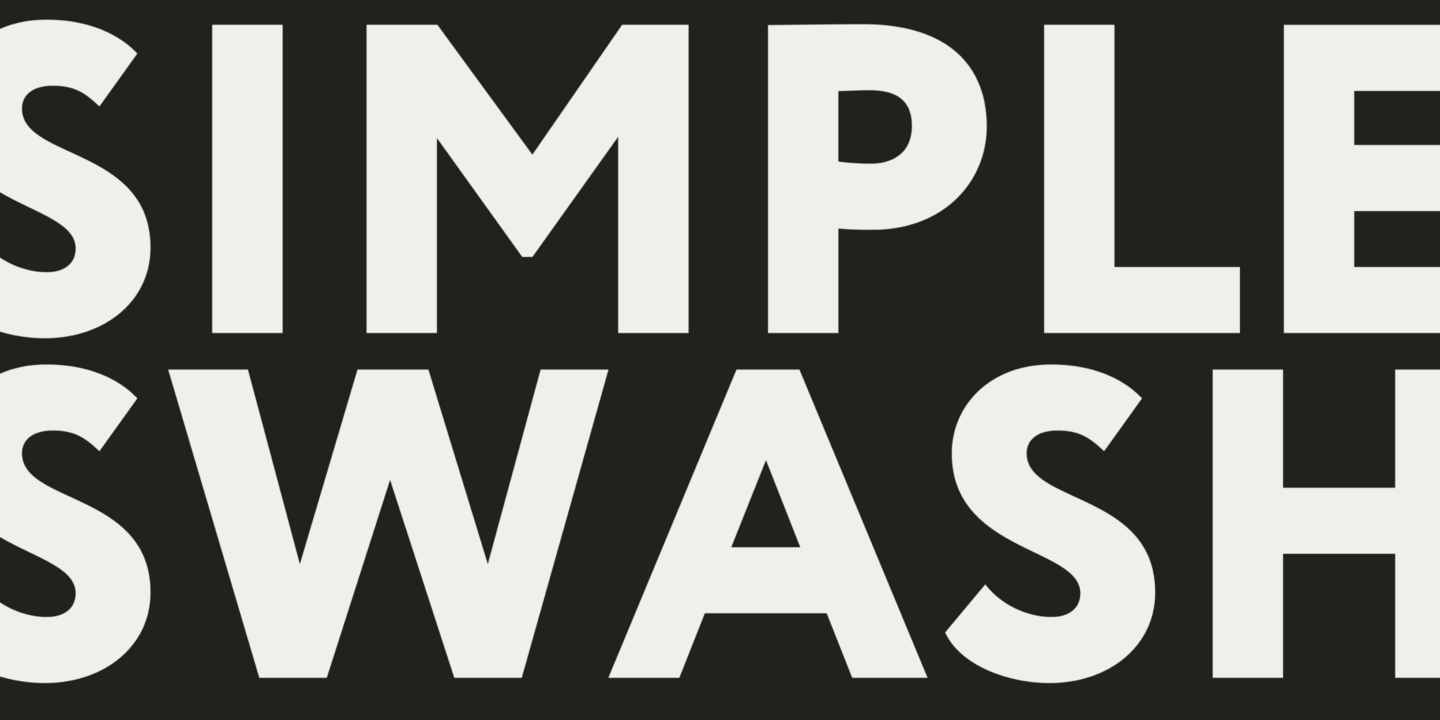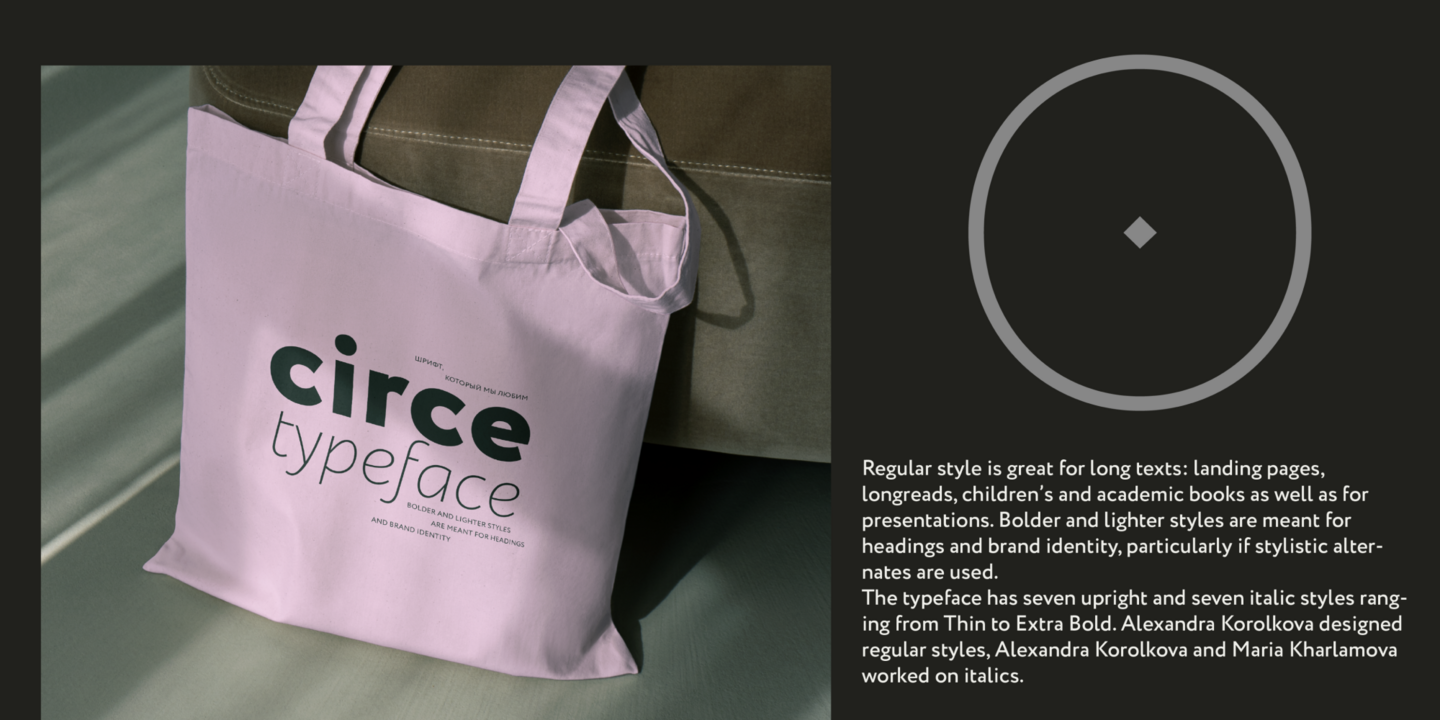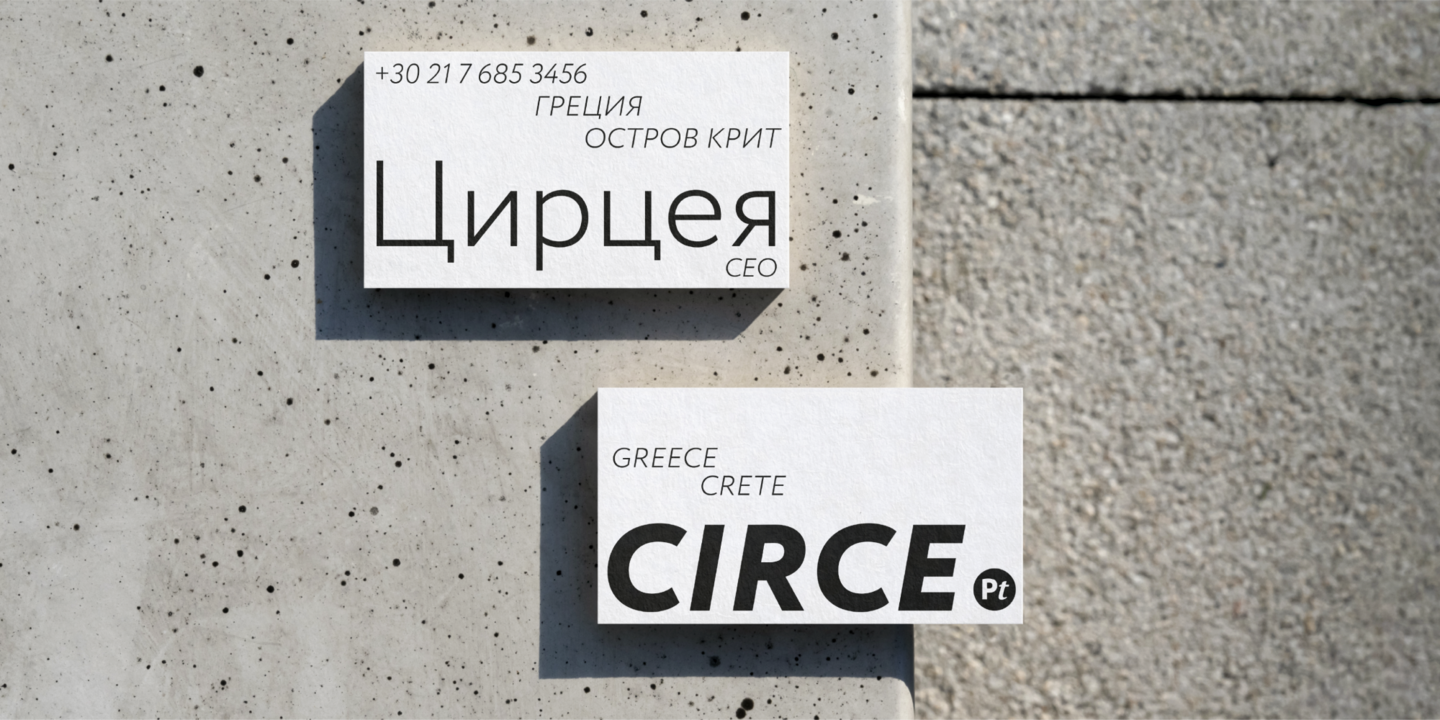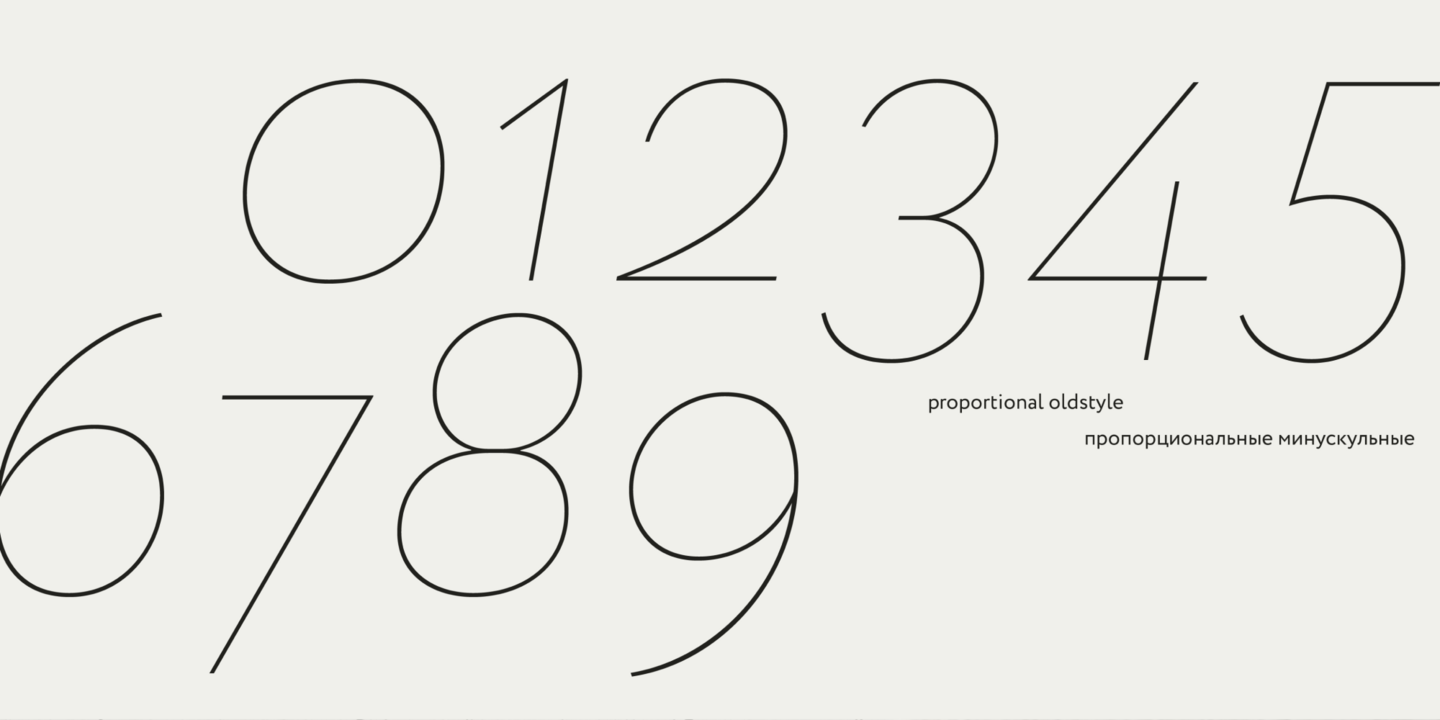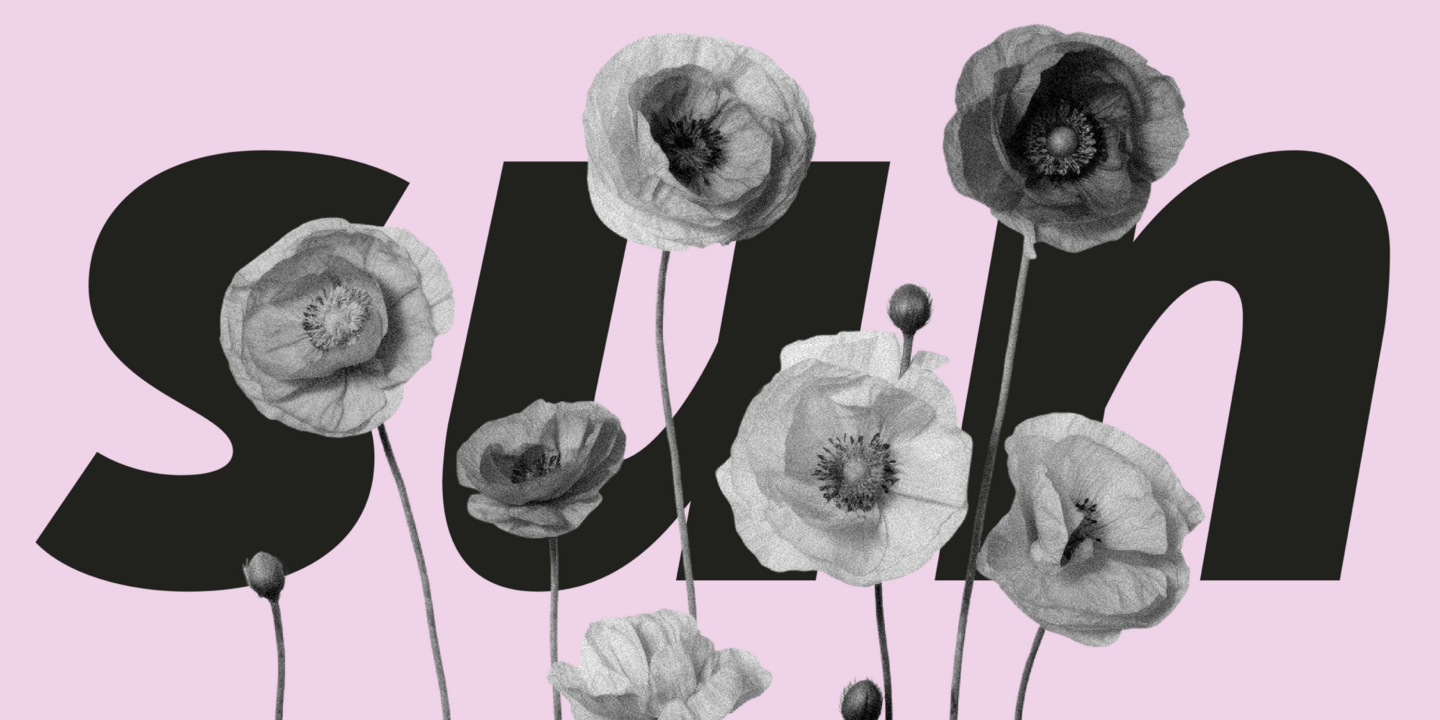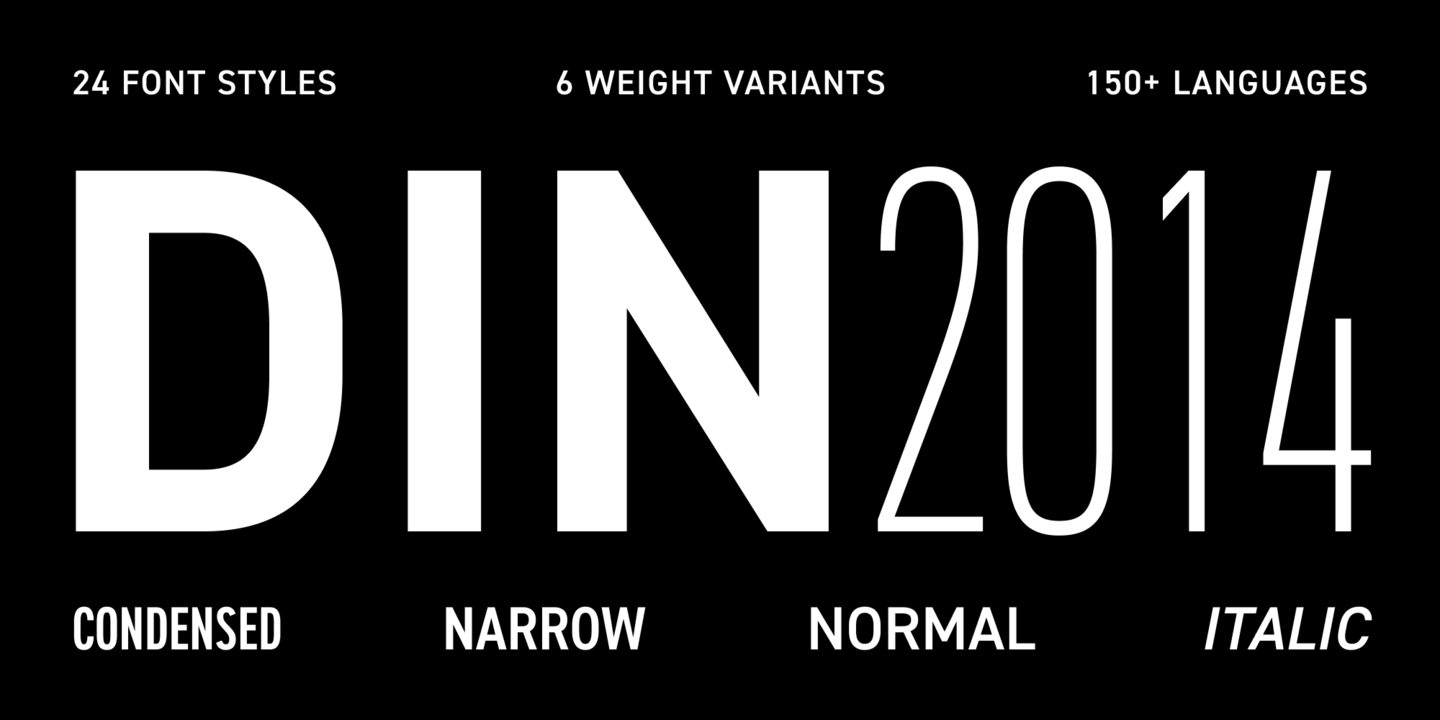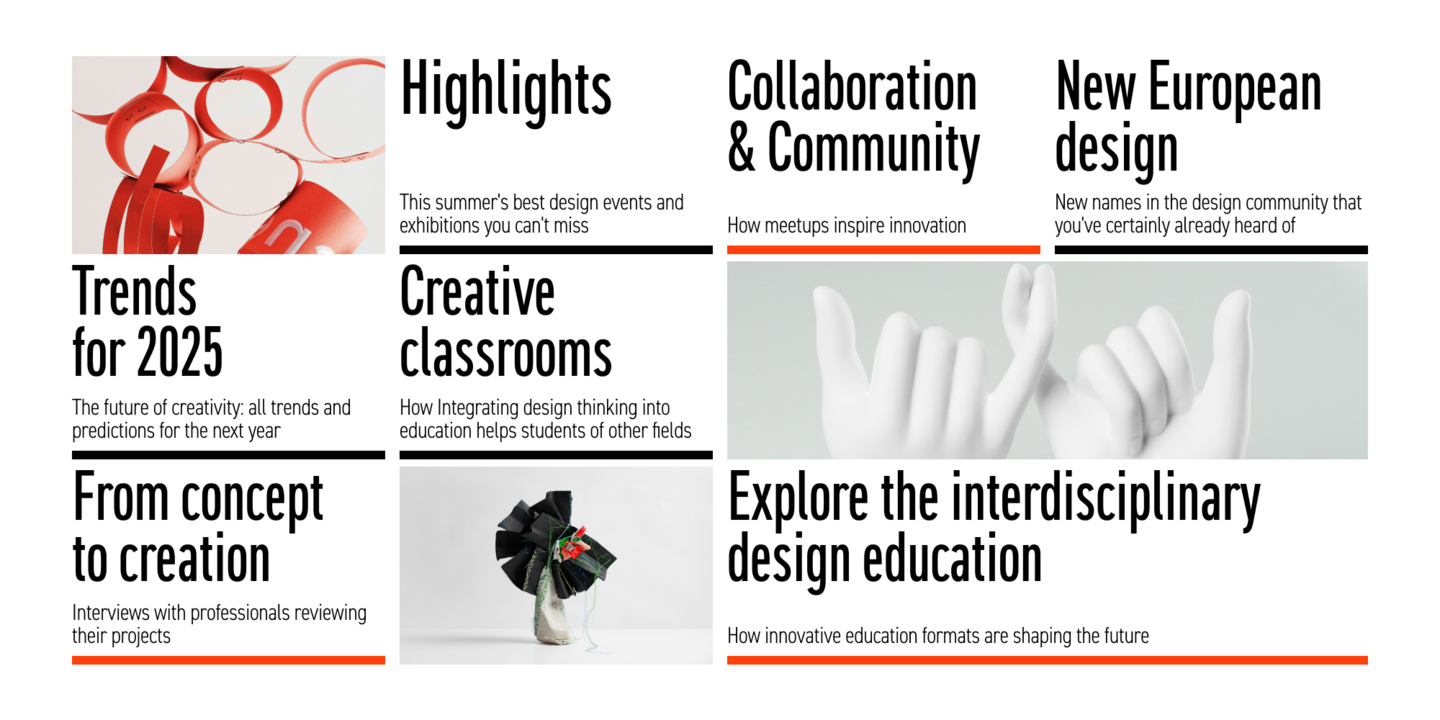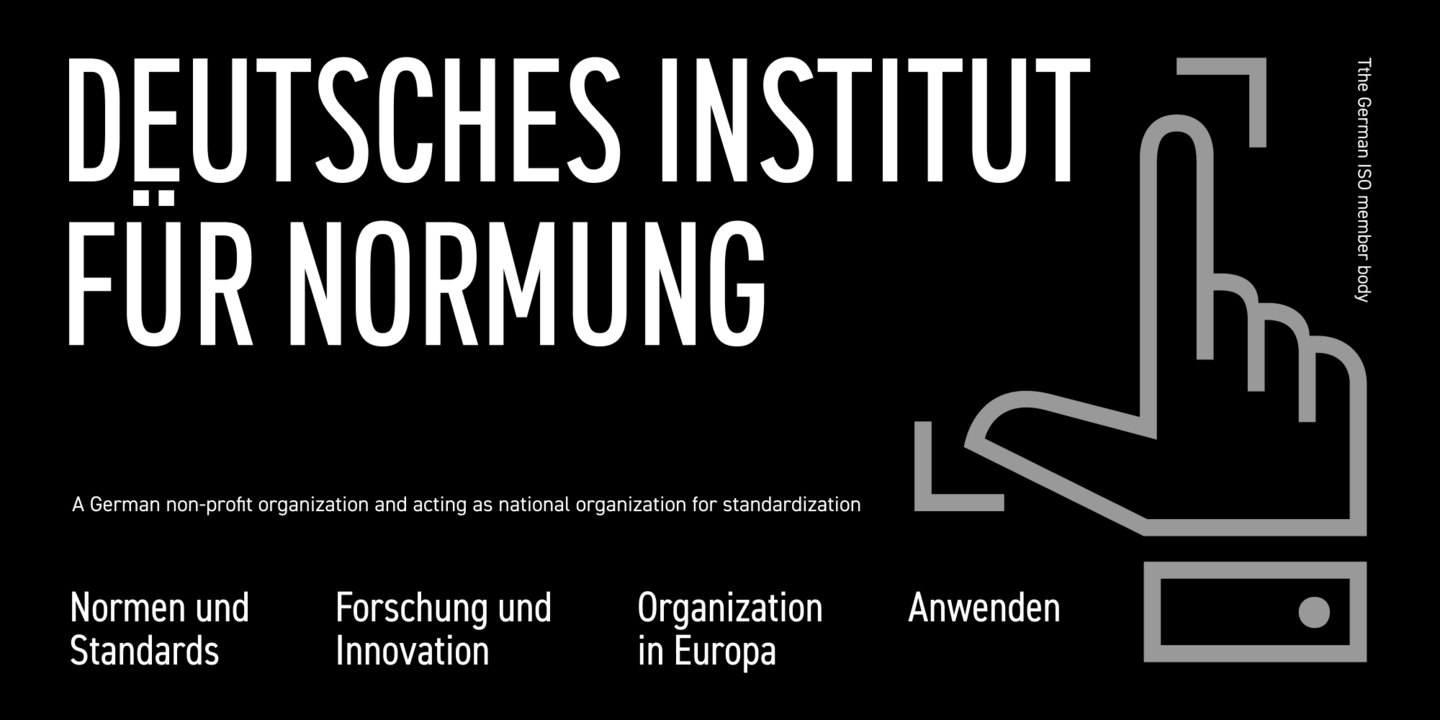
Police du paratype
Tout remonte aux années 1980, lorsqu'un petit groupe de dessinateurs de caractères et d'ingénieurs en informatique a saisi l'occasion de participer à la révolution de l'édition numérique. En combinant nos compétences en matière de caractères et de programmation, nous avons numérisé une vaste bibliothèque de police à l'encre sur papier, nous sommes passés à la conception et à la production de police entièrement informatisées et nous avons adapté nos polices à des dispositifs d'impression et d'informatique en constante évolution.
Circe - un grotesque géométrique sympathique avec de nombreuses options de personnalisation - est une police de caractères qui comprend sept styles droits et sept italiques véritables allant de Thin à Extra Bold. Le style normal convient bien aux textes longs, tandis que les graisses plus grasses et plus légères conviennent mieux aux titres et à la stratégie de marque. Chaque style vertical contient plus de 2 500 glyphs et plus de 30 caractéristiques OpenType, notamment des alternatives stylistiques, des petites capitales, des chiffres à l'ancienne, des flèches et des combinaisons de cartes. Circe est également livré avec un large ensemble de swashes, permettant de modifier facilement les caractères, et supporte plus de 150 langues.
Le DIN s'impose comme une police de caractères définissant le genre grotesque moderne et est en fait l'une des polices les plus populaires utilisées aujourd'hui. Le DIN 2014, en particulier, se distingue par plusieurs caractéristiques uniques telles qu'une gamme de styles étroits, des segments verticaux droits dans les ovales majuscules et minuscules, et la possibilité de basculer entre les styles oblique et italique par le biais d'un jeu stylistique. La famille principale de caractères DIN 2014, quant à elle, propose trois variations de largeur (Regular, Narrow, Condensed) et 24 styles. La DIN 2014 prend en charge plus de 150 langues, y compris les caractères latins et cyrilliques étendus.
Le Futura est un classique géométrique sans empattement, l'un des caractères les plus influents du XXe siècle. Paul Renner a présenté le dessin original pour Bauersche Gießerei (Bauer Types, SL) en 1927, basant son travail sur des formes géométriques simples pour refléter l'esthétique du constructivisme et du Bauhaus. Futura PT, la version cyrillique la plus complète de Futura, comprend 25 styles : huit droits, huit obliques et neuf condensés. Chaque style de caractère contient plus de 690 glyphs et 18 caractéristiques OpenType. Futura PT prend en charge plus de 150 langues.
Paratype
En 1998, nous avons décidé de séparer l'activité police de notre société mère de l'époque et de créer ainsi Paratype : une fonderie de caractères indépendante enregistrée en Californie. Dans les années qui ont suivi, nous avons considérablement élargi notre bibliothèque de police en créant de nouveaux caractères originaux et en rendant nos polices disponibles dans le monde entier via notre propre boutique en ligne et des canaux de distribution partenaires. À l'avenir, Paratype continuera à créer de nouvelles polices de caractères tout en s'engageant à fournir les meilleures solutions typographiques aux particuliers et aux entreprises.